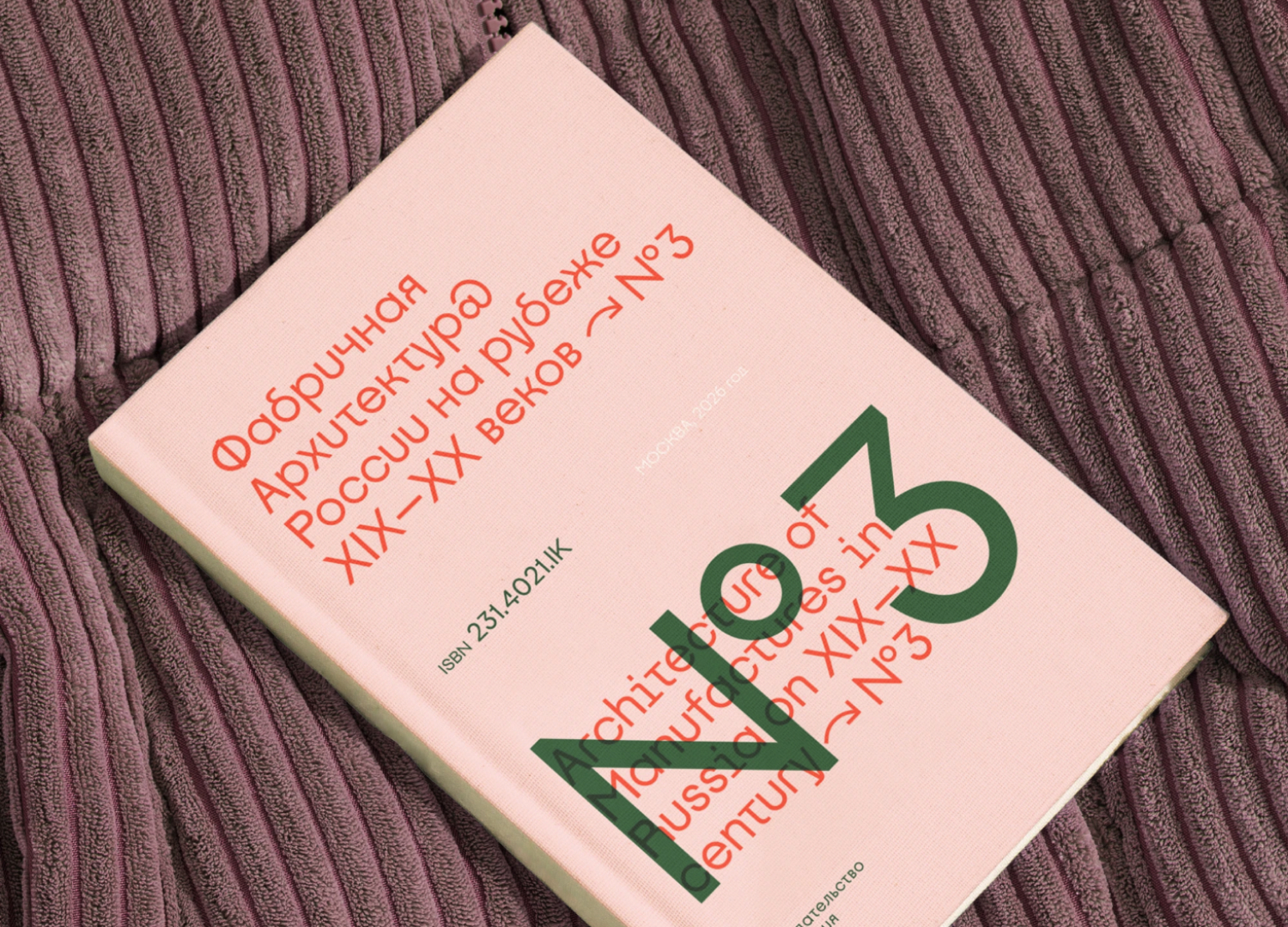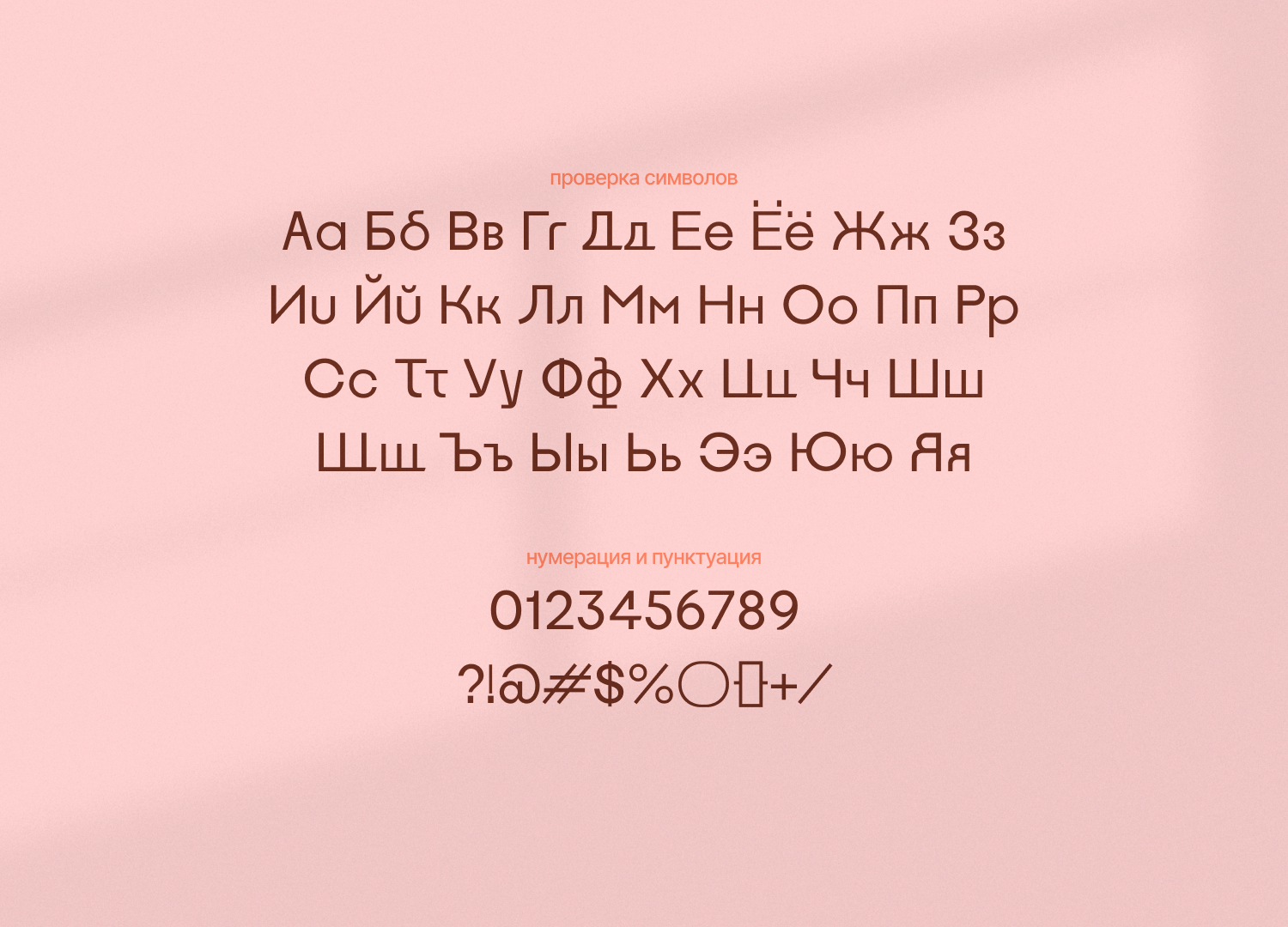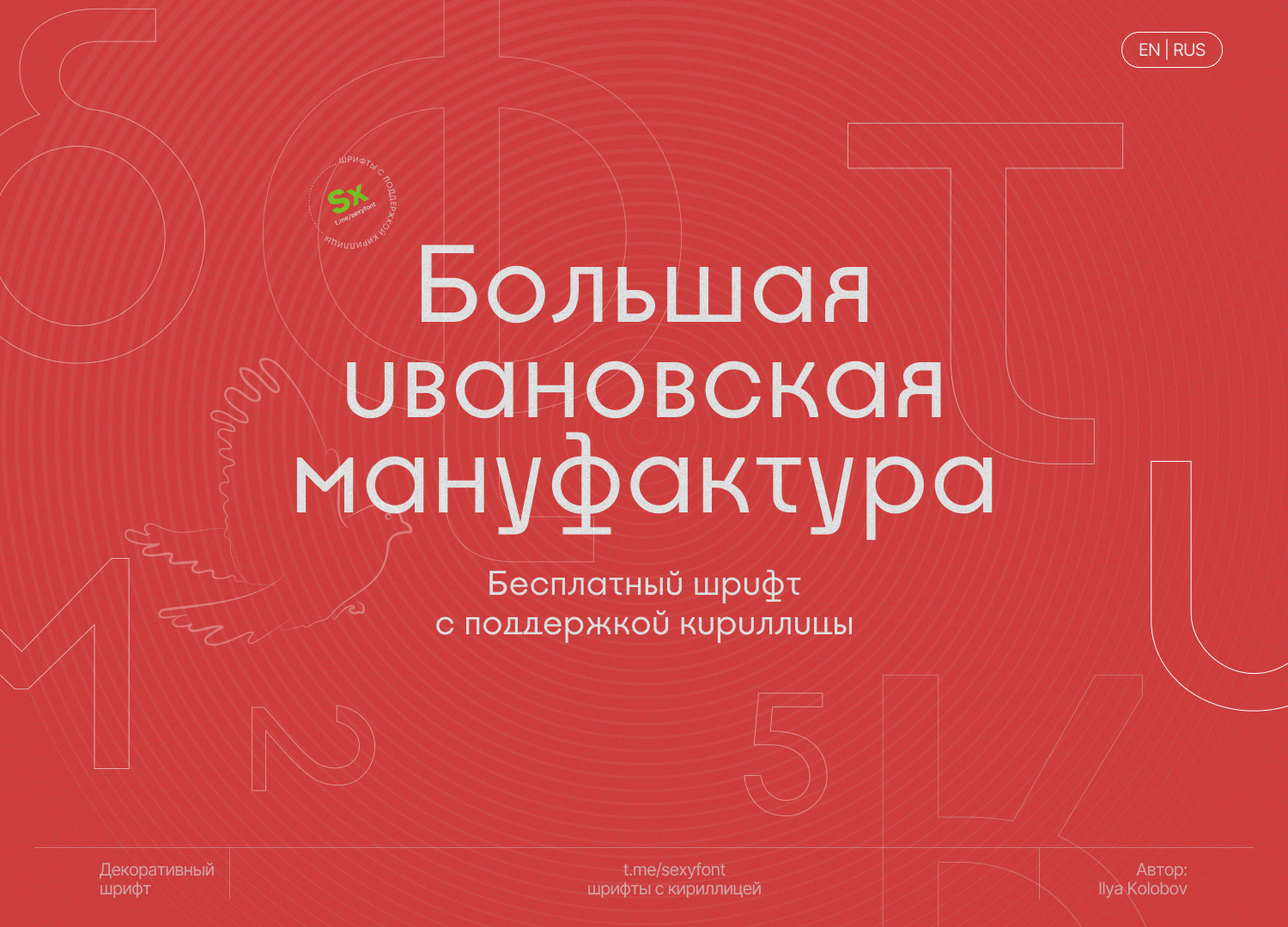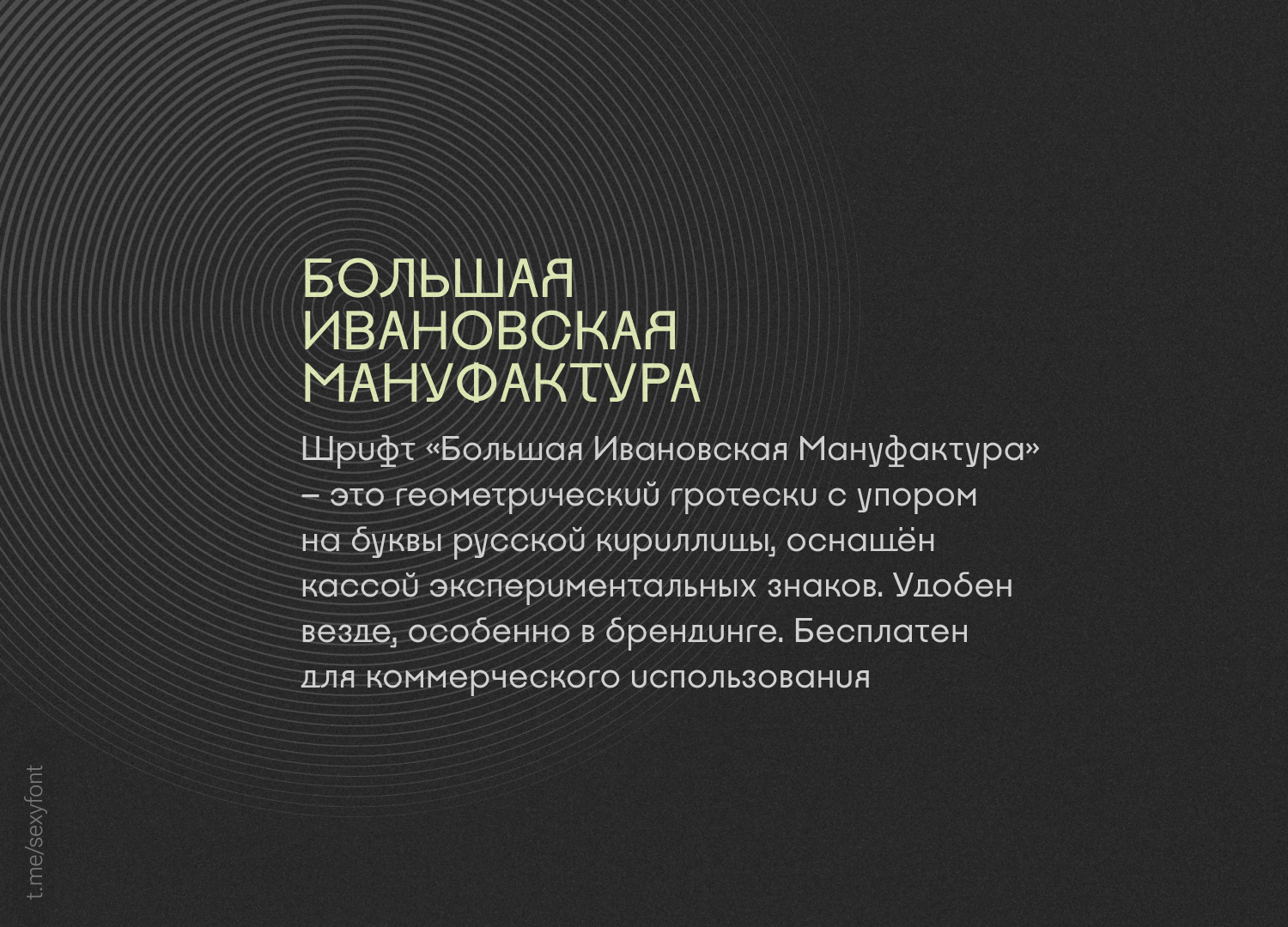
Бесплатный шрифт Bim «Большая Ивановская Мануфактура»
Шрифт Bim или «Большая Ивановская Мануфактура».Заценил его: читается легко, кое-где напоминает Soyuz, но без ощущения, что его уже юзали все дизайнеры на районе. Есть прикольные нестандартные символы, а ещё он абсолютно бесплатный — и для личных, и для коммерческих дел.Автор: Ilya Kolobov